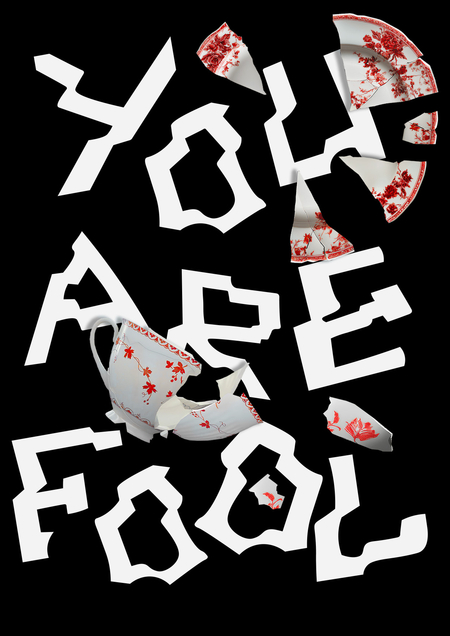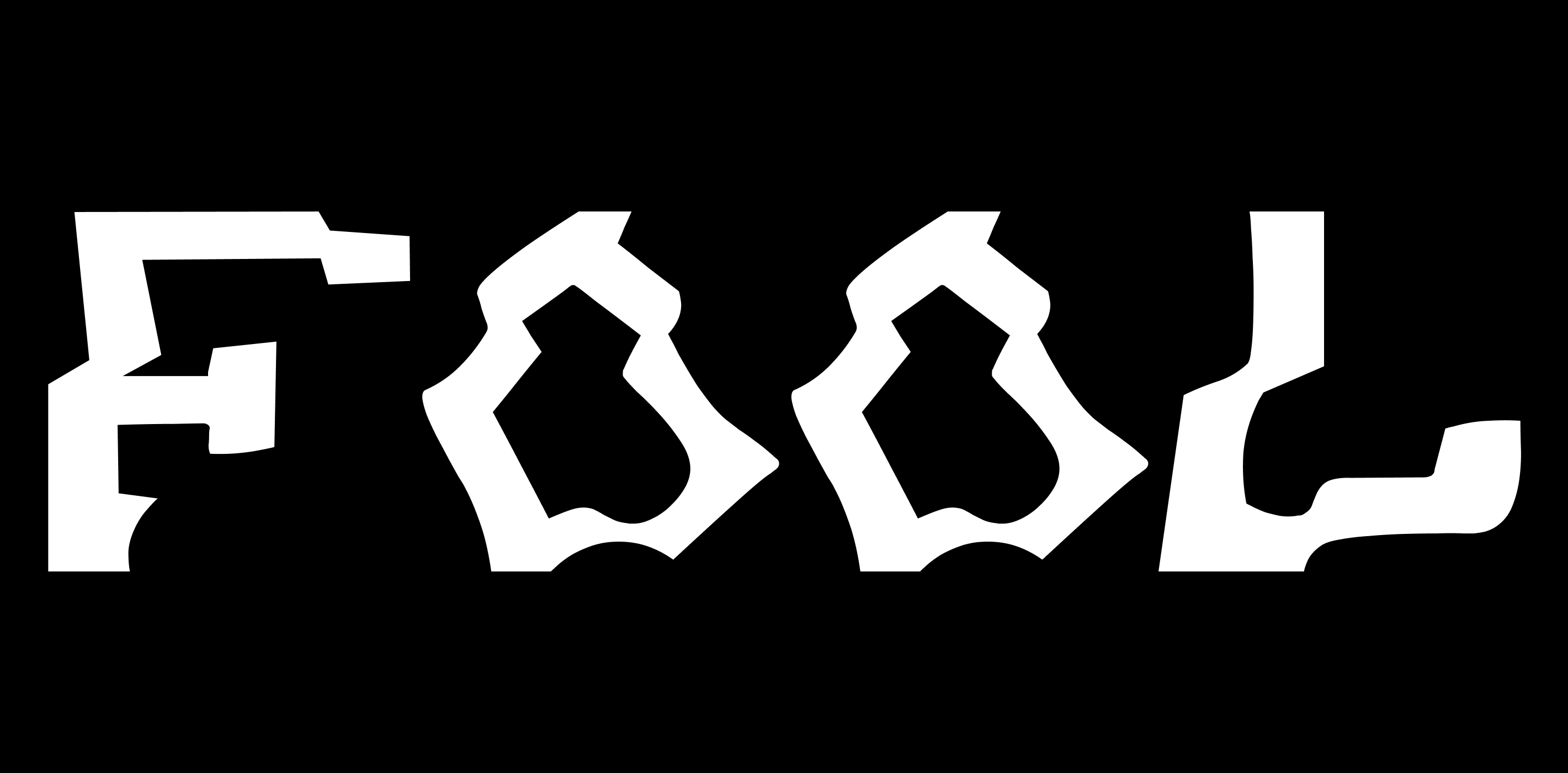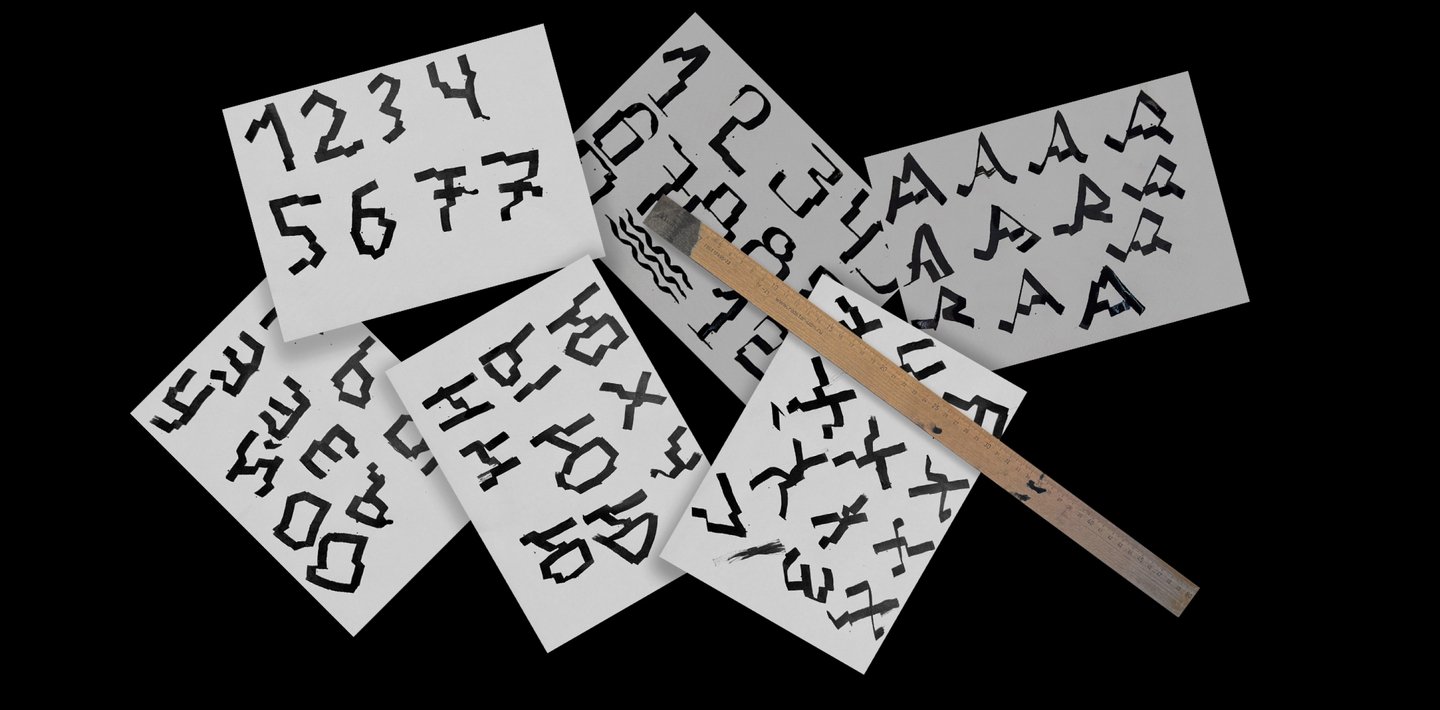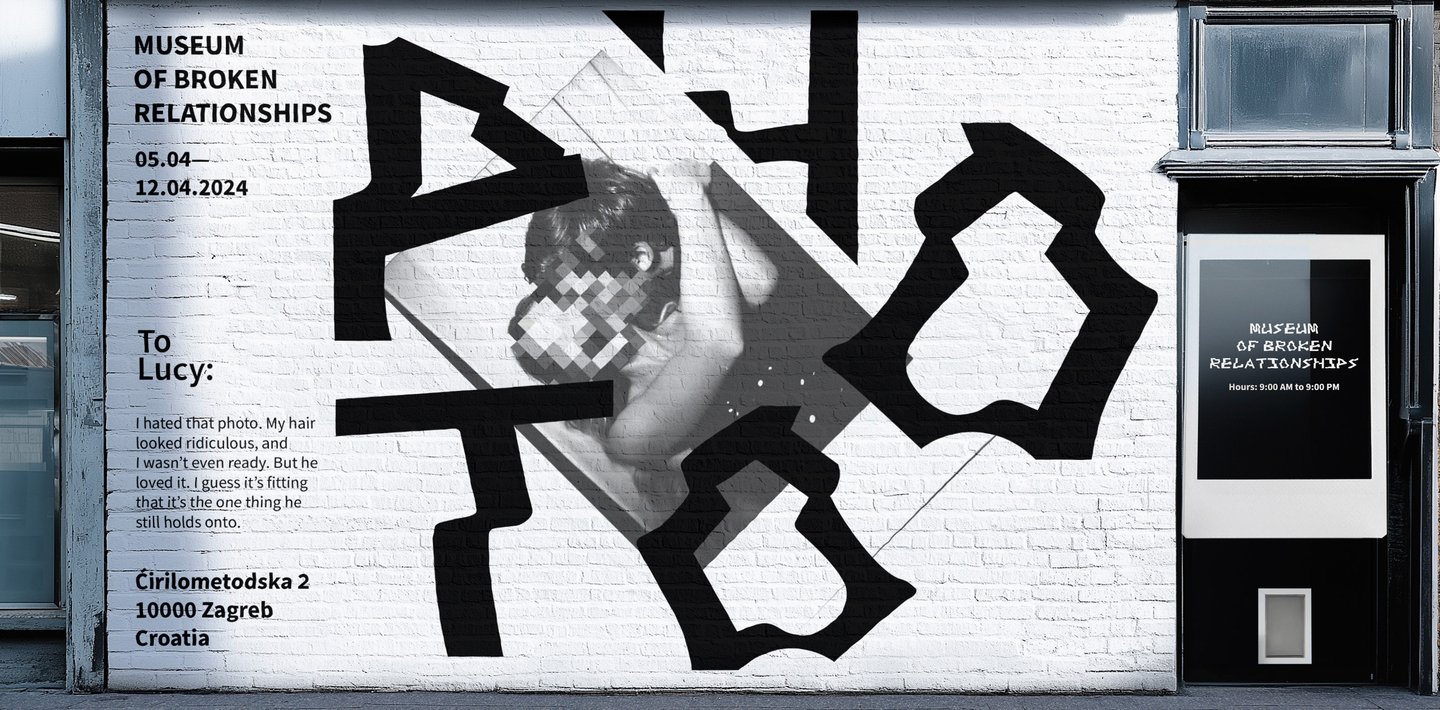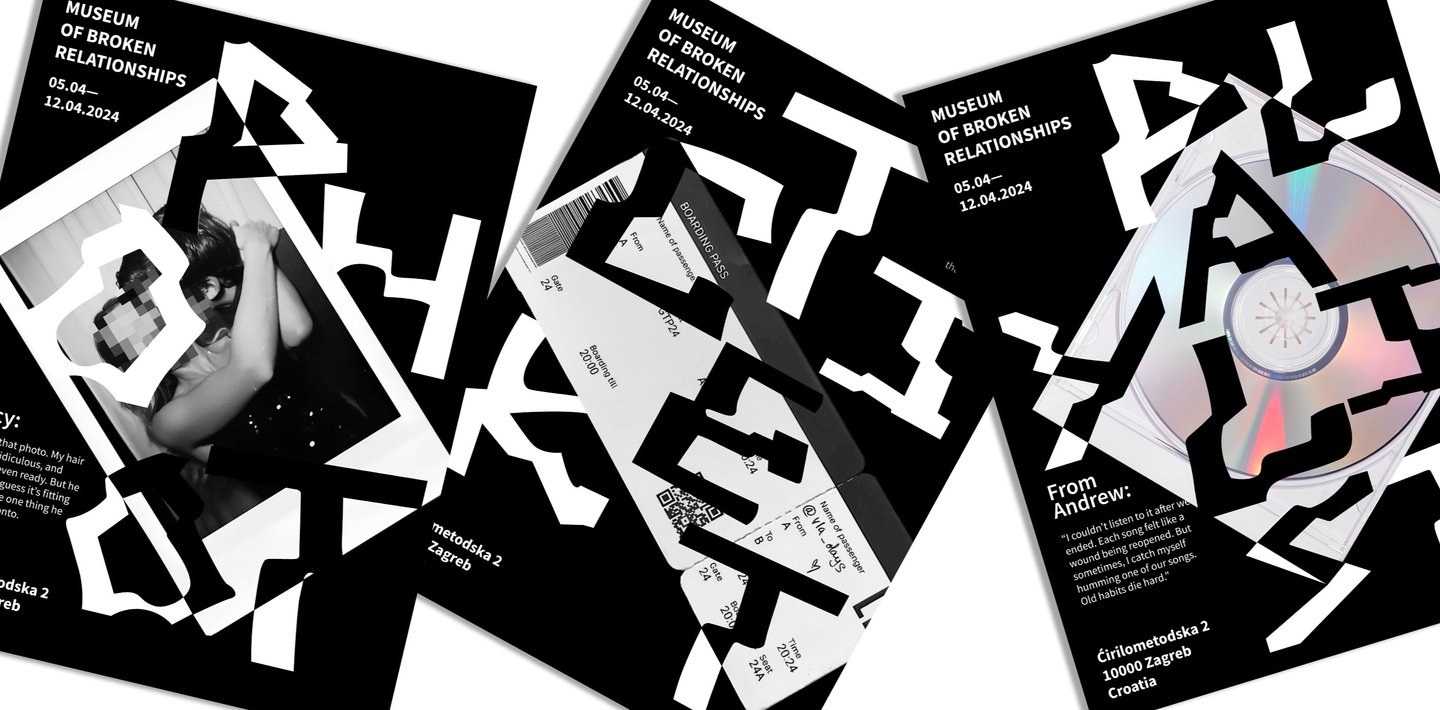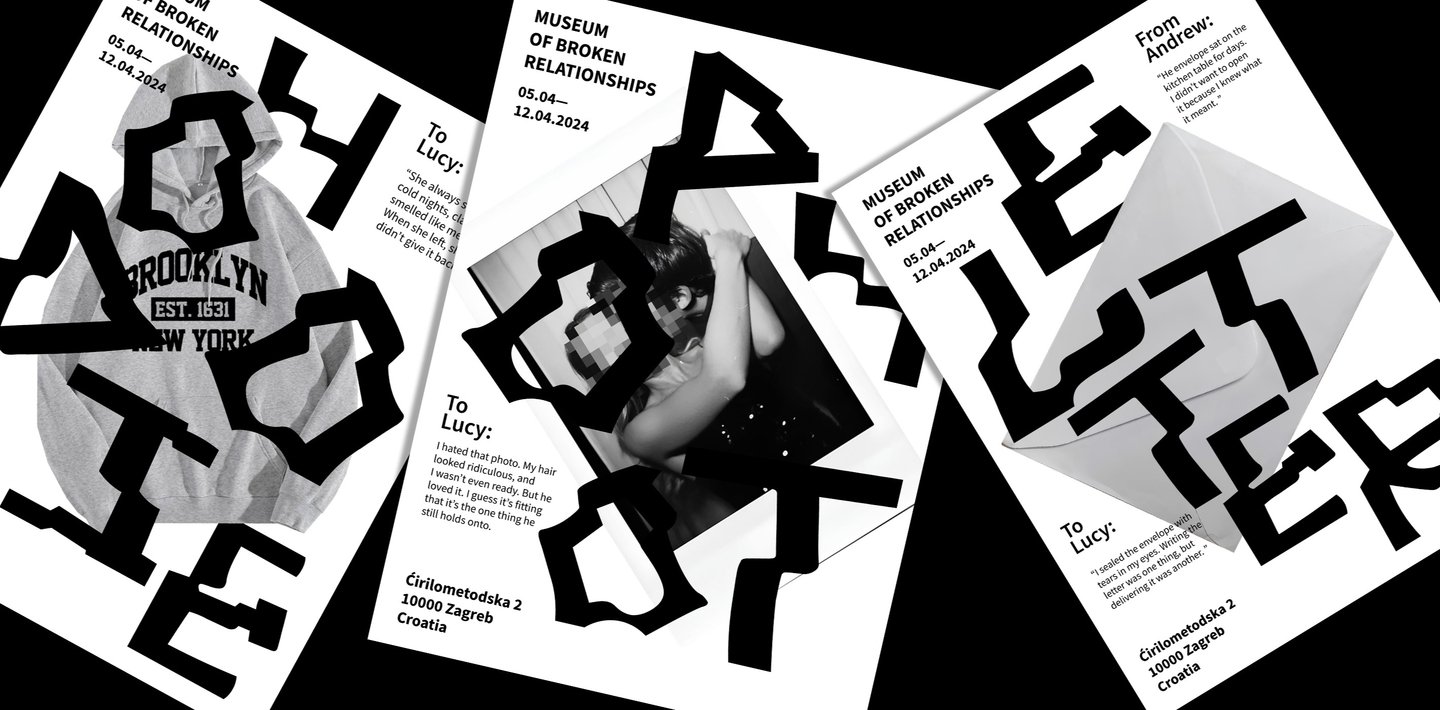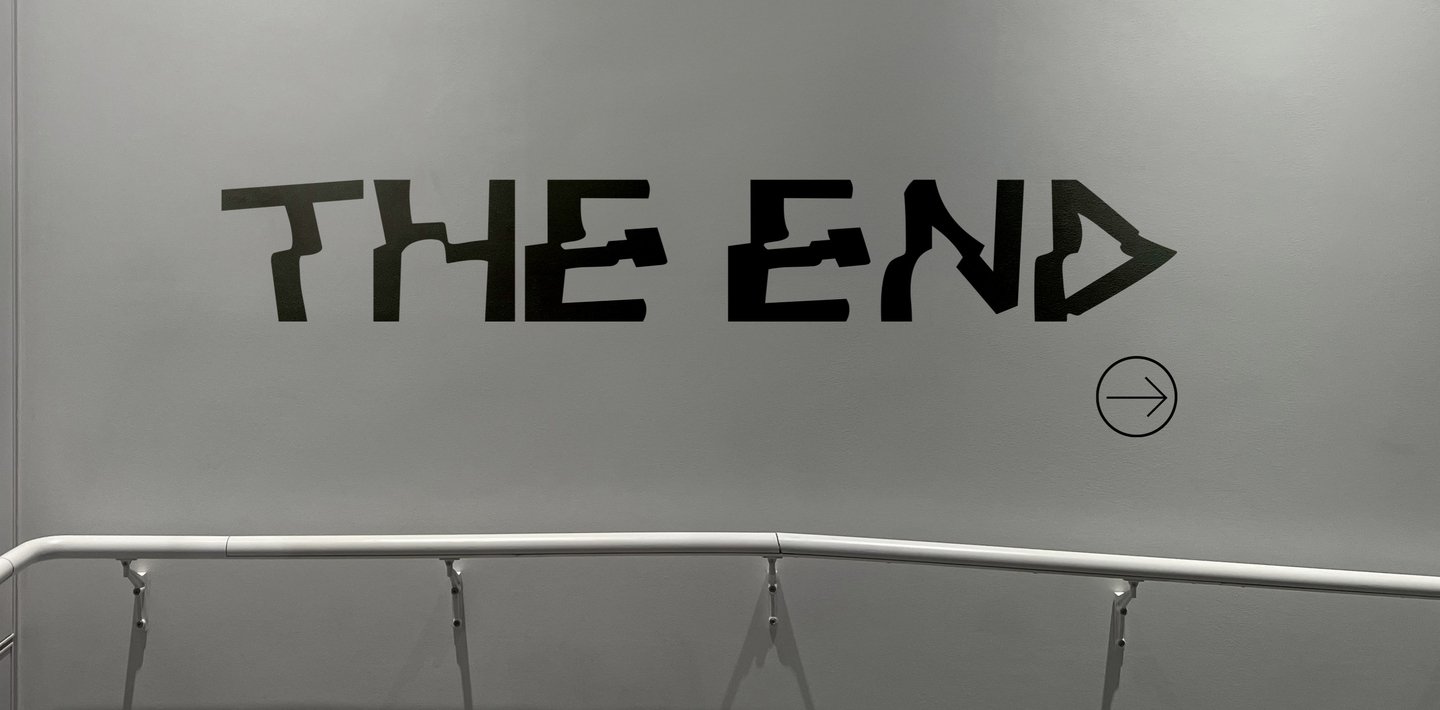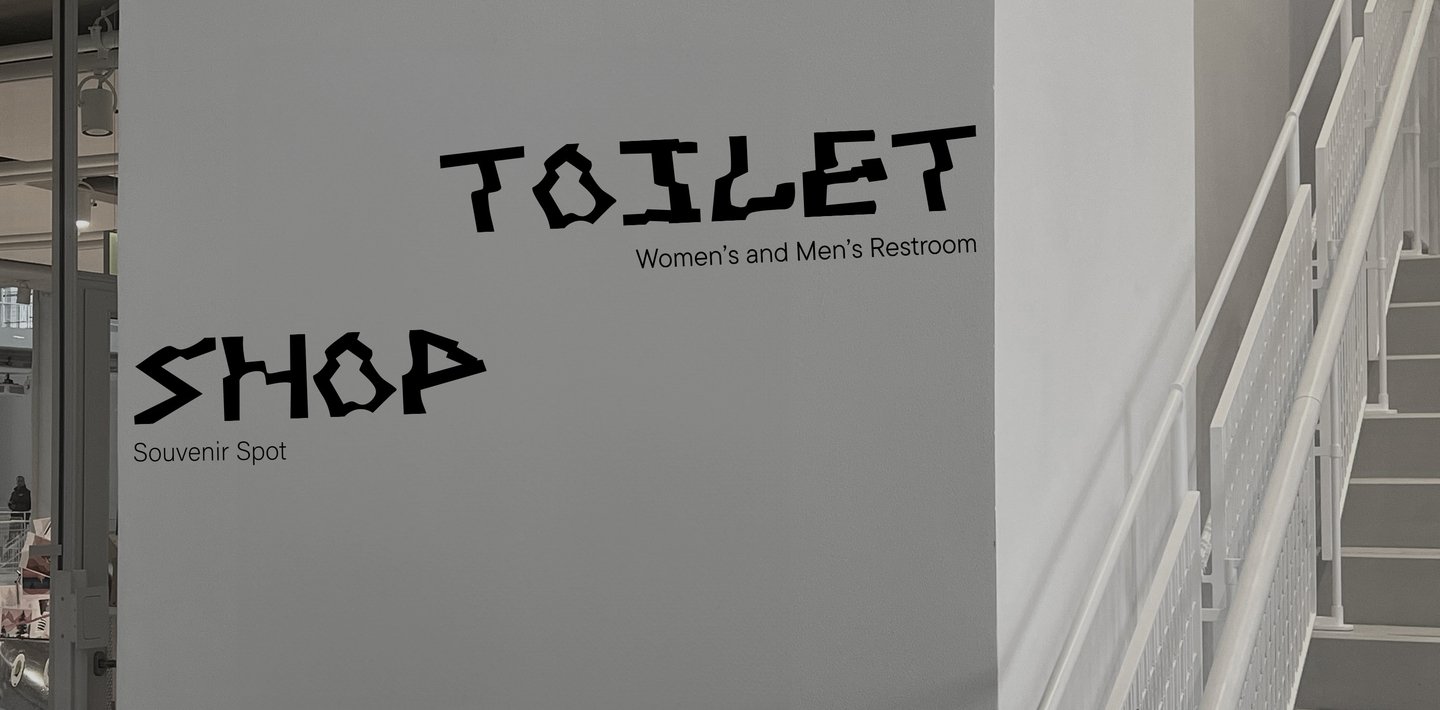
Разбитые отношения несут в себе надломы и несовершенства.
Каждое слово при ссорах напоминает о трещинах, разрывах и склеенных кусочках — как следы на сердце после утраты. Они неровные, но честные, словно голос, который дрожит, но говорит правду.
«Fool» — это название, которое символизирует момент, когда люди в ссоре переходят ту невидимую грань, после которой вернуть всё назад становится почти невозможно.
Оно подчёркивает, что в эти мгновения эмоции берут верх над разумом, а участники конфликта становятся «дураками» в попытках доказать своё, забывая о том, что действительно важно.